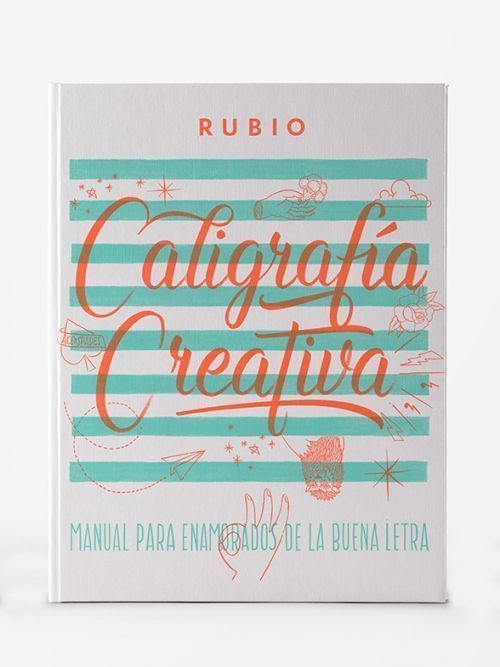
Un libro muy divertido y entretenido. Está en inglés pero tiene un montón de ilustraciones por lo que es fácil de entender. Es muy didáctico porque te enseña a hacer lettering a través de 40 ejercicios prácticos que puedes hacer en sus páginas interiores. Es un libro de lettering ideal para niños. Puedes comprarlo aquí.
LIBROS PARA APRENDER HAND LETTERING
Es un libro básico con una estética muy cuidada. Está en inglés pero viene con muchas ilustraciones que hacen que sea más fácil entenderlo todo. No entra mucho en detalles ni explica la técnica pero tiene muchos ejemplos de lettering que te pueden servir para inspirarte. También propone ejercicios y tiene tiene más de 100 páginas para practicar. Puedes comprarlo aquí.
El nuevo libro de Marta Velázquez de Happy Letters se ha convertido en uno de nuestros favoritos. Un manual donde encontrarás explicaciones paso a paso, de manera sencilla, y con preciosas ilustraciones a todo color. Un libro precioso, con un montón de ejercicios e ideas, que no podrás parar de hojear. Puedes comprarlo aquí.
Este libro es uno de los más vendidos. Te explica los materiales que necesitas, consejos, ejemplos para inspirarte y tiene páginas para practicar. También incluye un tutorial para digitalizar tu lettering usando Photoshop. Ahora han sacado la versión en español (ver siguiente libro). Puedes comprarlo aquí.
Versión en español del libro Creative Lettering & Beyond. Un libro muy completo donde te enseña y muestra ejemplos de caligrafía, lettering creativo, chalk lettering y más.En la primera parte explica las reglas para hacer caligrafía moderna y hay plantillas para practicar con plumilla. Tiene un capítulo de lettering ilustrado, otro para chalk lettering y por último ideas de manualidades con lettering. Lo que me gusta de este libro es la cantidad de explicaciones e ideas creativas para hacer con lettering. Puedes comprarlo aquí.
LIBROS PARA APRENDER CHALK LETTERING
Un libro imprescindible si quieres practicar Chalk lettering. Su autora Valerie es toda una eminencia en el tema y ha volcado todo su conocimiento en este libro. Es un libro muy completo donde aprenderás desde lo más básico del chalk lettering hasta a hacer composiciones. Además las tapas son duras y por dentro sirven para practicar con tizas! Puedes comprarlo aquí.
Un libro precioso y a la vez muy práctico para aprender los secretos del chalk lettering. Te encantará por su encuadernación de anillas y tapas duras con cantos reforzados que lo hacen muy fácil de usar. En su interior encontrarás todo lo que necesitas saber para aprender a hacer lettering con tizas: materiales, trucos, abecedarios… además de un montón de efectos, dibujos de flechas, flores, banners y muchas ideas. El libro está en inglés pero tiene muchas imágenes explicativas por lo que se entiende fácilmente. Muchos de los ejercicios e ideas los puedes hacer tanto con tizas como con rotuladores o acuarelas. Lo súper recomiendo 😉 Puedes comprarlo aquí.
LIBROS PARA APRENDER BRUSH LETTERING
El libro Letras Bonitas de ThreeFeelings se ha convertido en el libro de referencia para aprender brush lettering en español. Es un libro muy práctico, con plantillas para practicar directamente sobre el libro. Incluye tanto ejercicios para practicar con rotuladores Tombow de punta de pincel como con rotuladores Fudenosuke. Te encantará por su diseño, sus claras explicaciones y sus ejercicios con ejemplos inspiradores. Muy recomendable. Puedes comprarlo aquí.
Rubio – Español – Tapa dura – 152 páginas.
El nuevo libro de caligrafía de Cuadernos Rubio es muy completo. Me encanta su estética con un toque hipster y sus toques divertidos. Es un libro para practicar letras con lápices o rotuladores de punta pequeña. Incluye un montón de ejercicios que puedes hacer directamente en el libro y conforme vas avanzando, va subiendo de nivel.
Lo encontrarás aquí.
Three Feelings – Español – Tapa blanda – 207 páginas.
Si “Letras bonitas” está entre nuestros libros favoritos para aprender lettering con rotuladores, el segundo libro de Three feelings nos tiene totalmente enganchados. Te va a encantar por su estética tan cuidada, por lo fácil de las explicaciones, porque va un paso más allá y además de enseñarte a dibujar letras bonitas, también aprenderás a hacer sombras, degradados, composiciones y decorar tus letterings. En definitiva, un libro muy completo tanto si estás empezando como si quieres llevar tus letterings a otro nivel. Un imprescindible en tu biblioteca. Puedes compralo aquí.